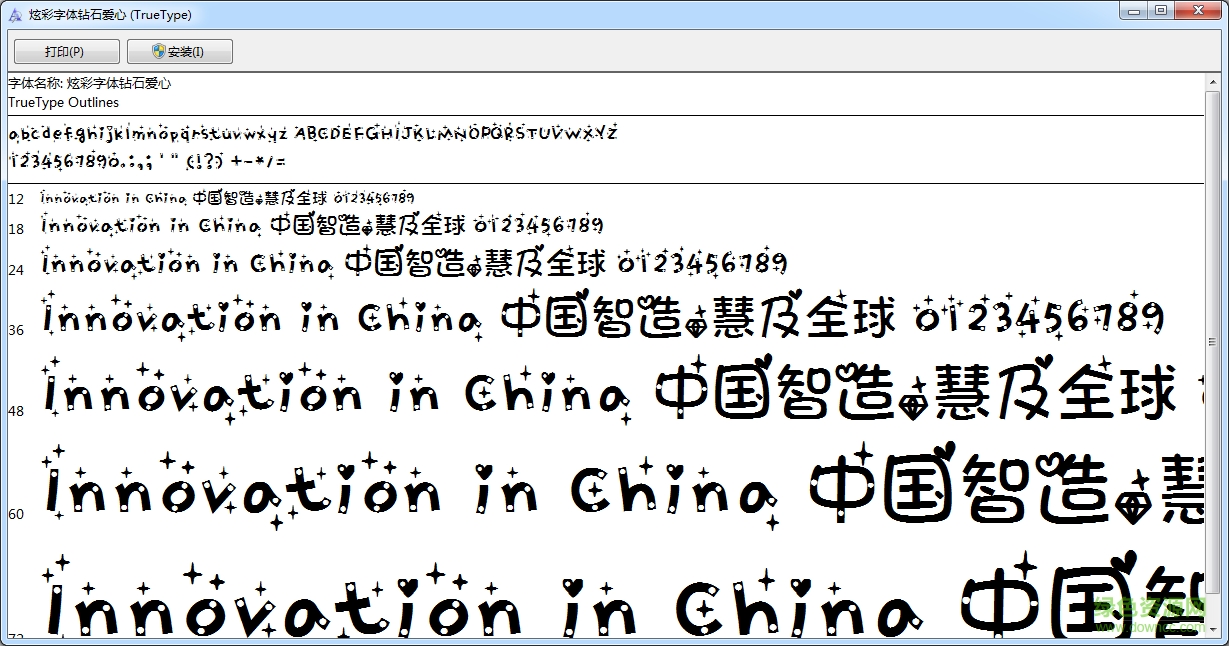
鉆石愛心炫彩字體是一款比較少女風(fēng)的電腦字體。字體非常美觀,做廣告設(shè)計(jì)、兒童宣傳海報(bào)時(shí)再適合不過了!小編特地為大家提供的詳細(xì)的字體安裝方法,歡迎用戶來綠色資源網(wǎng)下載使用!
鉆石愛心字體相當(dāng)?shù)目蓯?、呆萌!小編?qiáng)烈推薦給各位少女心比較重的網(wǎng)友下載使用哦!